Как добавить знаки ¿ и ¡ в рукописный шрифт
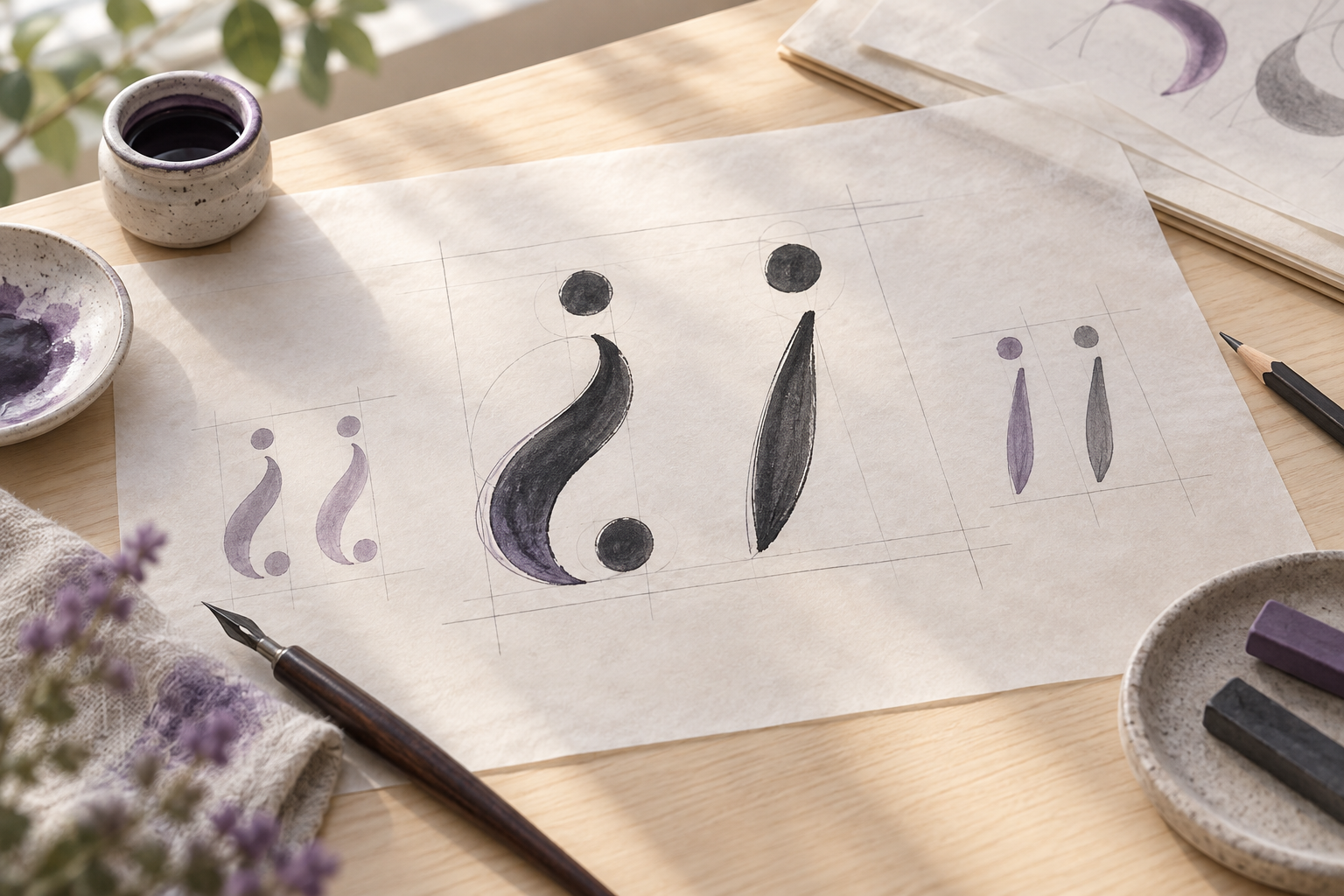
Открывающие знаки ¿ и ¡ показывают читателю, где начинается вопросительная или восклицательная часть испанского предложения. В рукописном шрифте им нужны собственные Unicode-ячейки, ясный поворот формы и согласованная пара с обычными ? и !. Ниже — практический план: от проверки набора и рисунка до теста в строках, макете и экспортированном файле.
Почему эти знаки нужно проектировать отдельно
В испанском письме вопрос или восклицание обычно ограничивают парой знаков: открывающий ставят в начале соответствующей конструкции, а закрывающий — в её конце. Например: «¿Vienes mañana?» и «¡Qué sorpresa!». Если вопросительная часть занимает только фрагмент фразы, открывающий знак начинается у этого фрагмента: «Si tienes tiempo, ¿me llamas?». Это правило помогает увидеть границы интонации ещё до того, как читатель дошёл до последнего слова.
Для шрифта это означает, что одной пары ? и ! недостаточно. В наборе должны быть отдельные знаки U+00BF INVERTED QUESTION MARK (¿) и U+00A1 INVERTED EXCLAMATION MARK (¡). Unicode относит их к Latin-1 Supplement и отмечает испанское употребление; у ¡ в NamesList также указаны астурийский и галисийский языки. Не подменяйте их перевёрнутыми картинками, сделанными из закрывающих знаков: в тексте это другие кодовые позиции, и приложение запросит именно нужный символ.
Практическая задача дизайнера — сохранить узнаваемость при повороте, но не превращать знак в случайную букву, цифру или орнамент. Это особенно важно для шрифта из почерка: привычный жест автора может выглядеть эффектно отдельно, но сбивать распознавание в плотной строке. Проверять нужно сразу два уровня: рисунок каждого глифа и его поведение рядом с латинскими буквами, пробелами, обычными вопросительным и восклицательным знаками.
Сначала проверьте, какие знаки действительно нужны
Перед заполнением шаблона зафиксируйте язык и предполагаемые сценарии. Если шрифт предназначен только для коротких русских надписей, испанские знаки могут не входить в первую версию. Если же проект обещает поддержку испанского текста, переведённых материалов или многоязычного бренда, открывающие знаки нужно включить в план до экспорта, а не добавлять после обнаружения пустого квадрата.
Соберите короткий перечень обязательных символов и отметьте их состояние: запланирован, нарисован, извлечён, проверен в файле. Добавьте четыре знака — ¿, ?, ¡ и ! — как связанную тестовую группу. У открывающих знаков собственные ячейки и кодовые точки; похожесть контура на перевёрнутый закрывающий знак не означает, что символ уже поддерживается.
Для технической проверки полезно записать кодовые обозначения рядом с видимыми знаками. В редакторе или проверочном тексте используйте сами символы, а в таблице проекта подпишите их как U+00BF и U+00A1. Так вы отличите отсутствие глифа от проблемы ввода или копирования текста. Официальные таблицы Unicode для Latin-1 Supplement показывают названия и кодовые позиции; рекомендации RAE по испанской орфографии описывают парное употребление знаков.
Как построить форму открывающего знака
Начните с чернового сравнения закрывающего ? или ! в вашей гарнитуре. Спросите себя, какие признаки делают его узнаваемым: характерная верхняя часть, дуга, точка, ширина, наклон, толщина штриха и связь с базовой линией. Затем нарисуйте открывающую форму с учётом того, что визуальный поворот должен быть понятен, а не механически зеркален. У рукописного знака может быть естественная асимметрия: сохраняйте её, если она не стирает отличие между вопросительной и восклицательной парами.
У ¿ особенно важны верхний крючок и нижняя точка. Слишком короткий верх превращает его в похожую на запятую деталь; слишком крупная нижняя точка утяжеляет конец знака и перетягивает строку. Сравните её с точкой закрывающего вопросительного знака: общий почерк может быть тем же, однако размер и оптическое положение должны работать в перевёрнутой ориентации.
У ¡ нет вопросительной кривой, поэтому не делайте её копией ¿ с заменённой точкой. Соотнесите штрих с обычным !: длину основного элемента, толщину, характер окончания и форму точки. Если закрывающий знак в шрифте имеет лёгкий наклон или рукописную неровность, открывающий может её повторить. Важно, чтобы при чтении «¡Hola!» глаз сразу видел пару, а не две разные стилистические системы.
Удобно поставить четыре глифа в одну строку и оценить их попарно: «¿Qué?», «¡Bien!», затем последовательно ¿ ? ¡ !. В первом тесте смотрите не на художественную выразительность, а на узнавание и баланс. Сравните высоту, боковые поля, плотность штриха и положение точек. Открывающие знаки часто визуально оказываются тяжёлыми внизу или слишком широкими; исправляйте конкретную причину, а не только субъективное впечатление «неаккуратно».
Интервалы: знак работает в контексте
Проверяйте открывающий знак перед строчной и прописной латинской буквой, после пробела и после слова. Составьте пары вроде «¿a», «¿Cómo», «¡alto» и «¡Atención». Между открывающим знаком и первым словом обычно не вставляют пробел: пробел разделил бы маркер начала и саму конструкцию. Убедитесь, что боковые поля это учитывают и знак не прилипает к следующей букве.